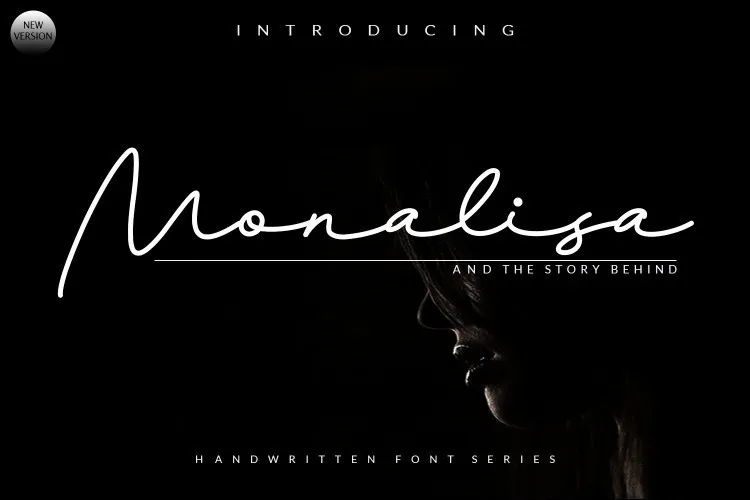
Monalisa Signature Font – Download Grátis
Esta é uma fonte escrita a mão assinada perfeita para aqueles que desejam adicionar um toque moderno aos seus designs. O Monalisa Font tem um aspecto leve e casual, com uma linha de base suave. Ideal para aplicar em cartões de aniversário, materiais de marca, cartões de visita, citações, panfletos e muitos outros formatos de design. Este estilo charmoso é perfeito para personalizar sua identidade visual pessoal ou profissional – seja uma assinatura única para seu blog ou até mesmo um logo inovador. Se você estiver criando cartões postais para seus convidados de casamento, a Monalisa Font certamente irá complementar o design com elegância e sofisticação. Além disso, esta fonte é muito versátil e pode ser usada em qualquer formato visual – seja impresso ou digital – tornando-a uma opção imprescindível para designers gráficos.